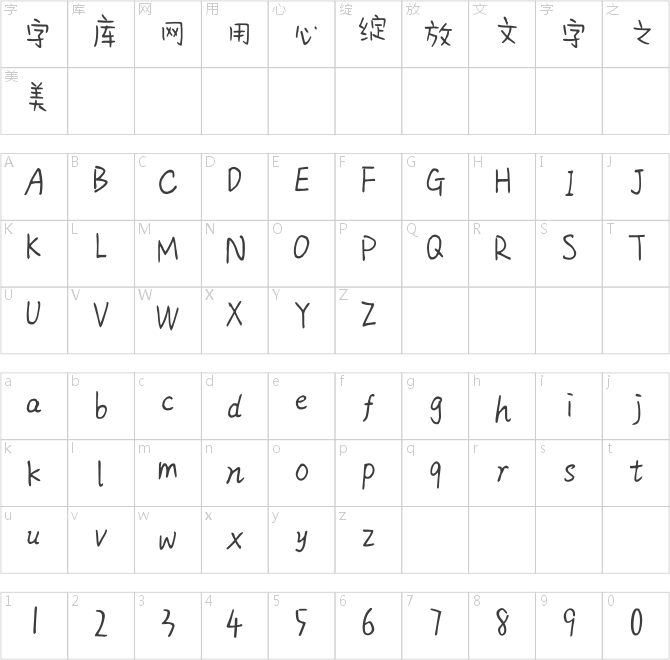
漢儀不一體字體下載BuYiTi不一體
漢儀不一體字體BuYiTi不一體字庫(kù)是一款讓人賞心悅目、百看不厭的中文字體,適合各類(lèi)廣告和產(chǎn)品包裝設(shè)計(jì)應(yīng)用,字體大小5.05MB,格式為ttf字體,上傳用戶(hù)是FaYu,作者/版權(quán)方為漢儀字庫(kù)